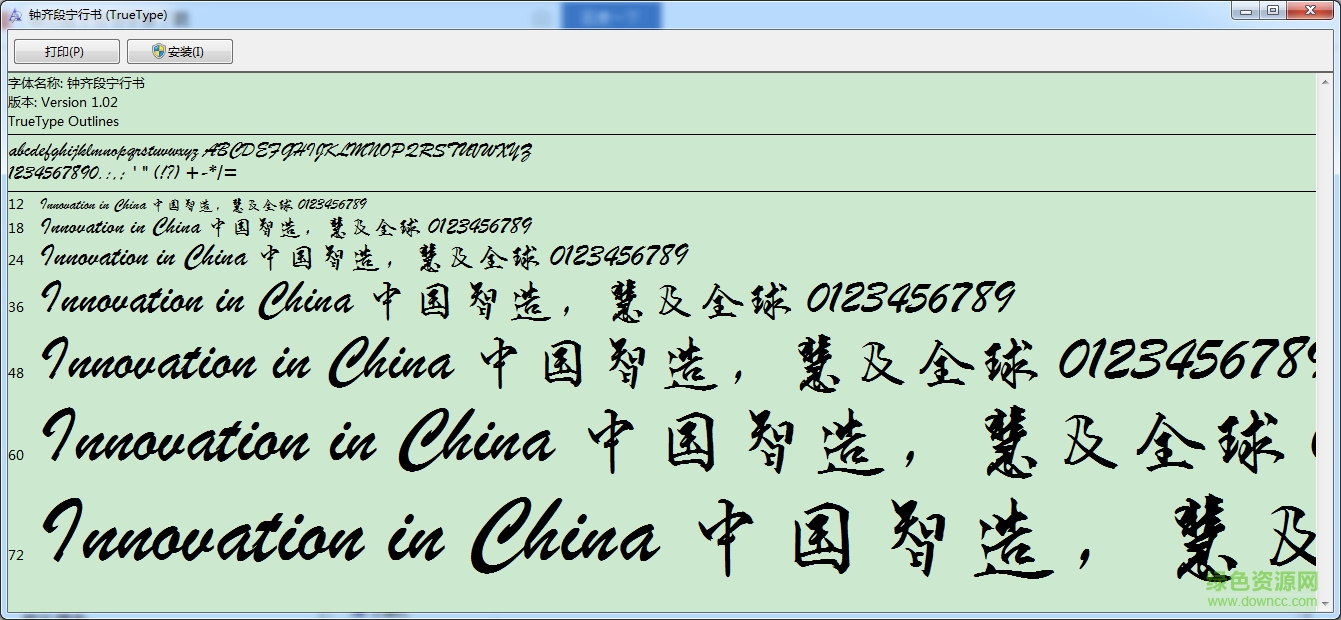
duanning-xing字體又叫鐘齊段寧行書字體,這款書法字體非常有神韻,濃淡相融得恰到好處,整體風(fēng)格和諧統(tǒng)一,實用性與藝術(shù)性兼?zhèn)?,歡迎大家免費下載!
有:橫(短橫、左尖橫、右尖橫等)、豎(懸針豎、短豎、垂露豎)、撇(短撇、豎撇等)捺(橫捺、反捺、短捺)、點、提(豎提等)
在書寫過程中,筆毫的使轉(zhuǎn),在點畫的各種形態(tài)上都表現(xiàn)得較為明顯,這種筆毫的運動往往在點畫之間,字與字之間留下了相互牽連,細(xì)若游絲的痕跡,這就是絲連。